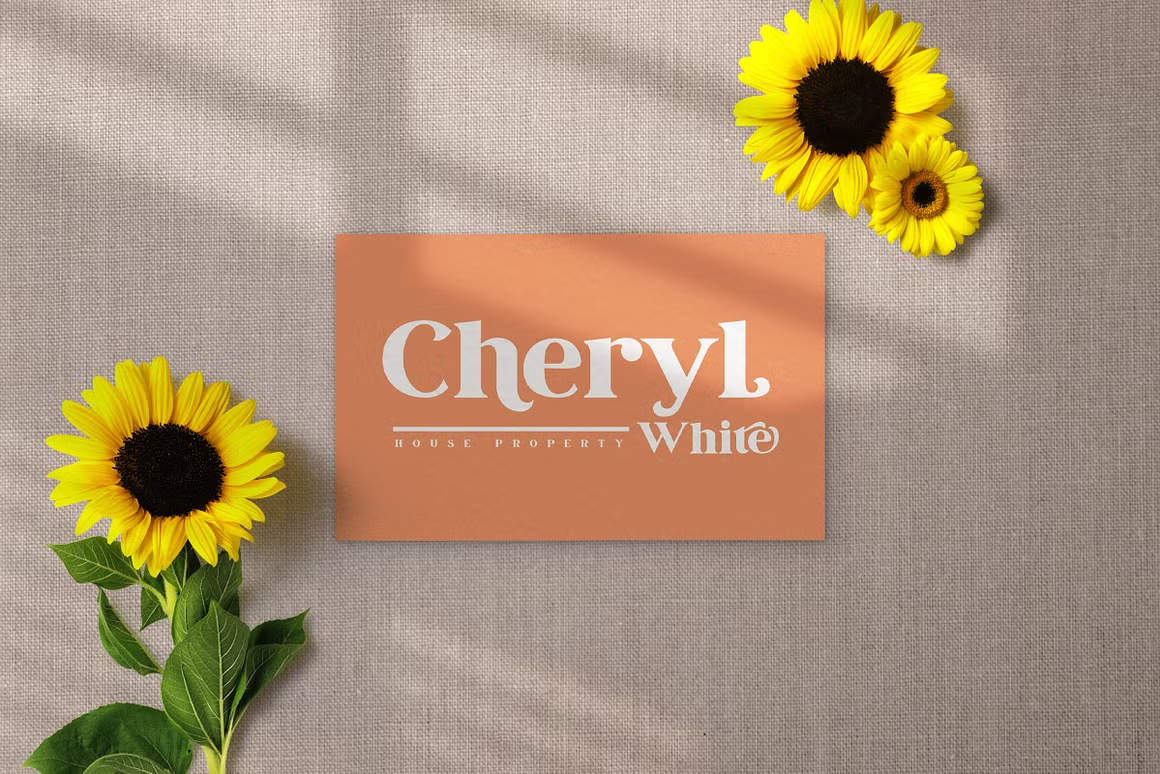
March Font
Description de March Font
La police March est une police d’affichage (Serif) moderne et épurée créée par notre talentueux concepteur de polices. Le design de la police rendra votre design plus beau et plus inspirant. Cette police conviendra à divers designs, tels que des affiches, des bannières, des logos, des couvertures de livres, des titres, des produits imprimés, des marchandises, des réseaux sociaux, etc. Regardez l’aperçu pour découvrir d’autres façons d’utiliser cette police.
Caractéristiques :
Accents (caractères multilingues)
66 suppléants
Chiffres et ponctuations